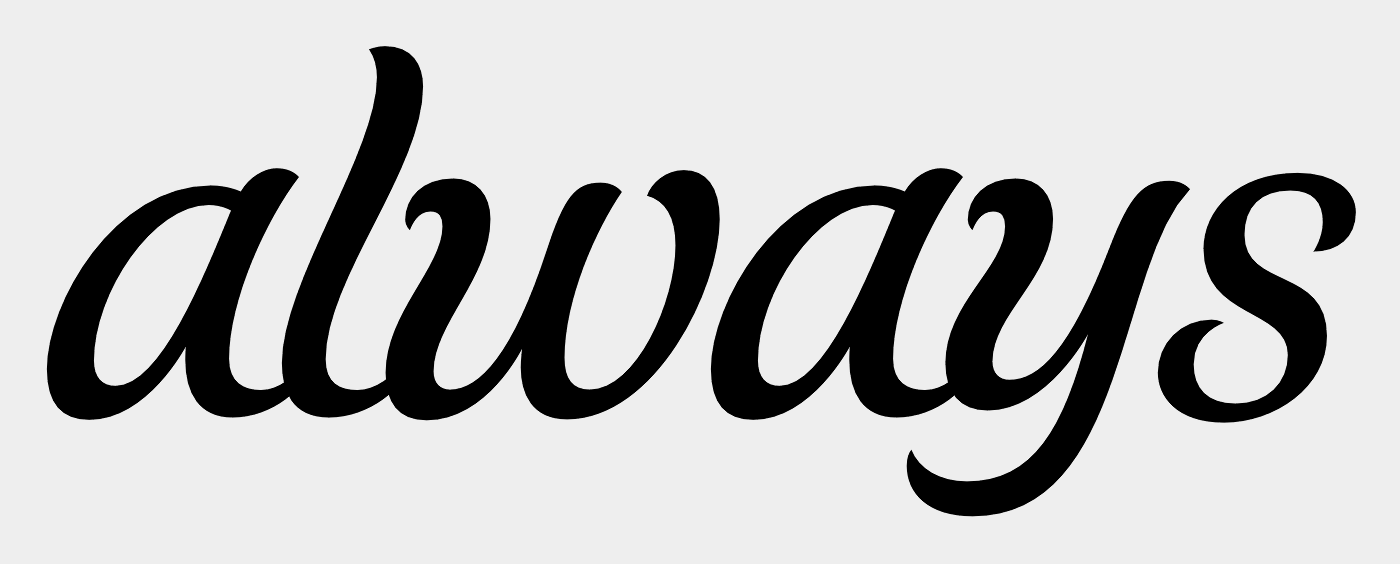
Suche Schriftart - ALWAYS ULTRA (BINDEN) LOGO
Könnt ihr mir vielleicht helfen? Ich suche diese oder eine ähnliche Schrift.
Wer sagt eigentlich, dass da überhaupt ein Font dahinter stecken muss.
Gut mnöglich, das die einen Grafiker beauftragt haben, der das noch so ohne Font schreiben kann, sind ja gerade einmal 6 Buchstaben, und auch die Buchstaben eines ganzen Fonts hat ja mal ein Mensch gezeichnet, dann sogar hunderte, die alle zusammen passen müssen.
Ich hab da mal die a übereinander gelegt:post-22079-0-17851100-1460199371_thumb.p
Die Formen sehen in der Tat sehr nach Kollege Jocham aus (wie schon in Gizzmos Link erwähnt) und wahrscheinlich hat er das Logo sogar gezeichnet!?
Nachdem ich Hubert Jochams Logos gesehen hatte - wirklich alles Top-Marken auch noch - würde ich das auch sehr vermuten - ist zu ziemlich die typische Handschrift.
Zudem, auch das Schoko-s ist nah dran.